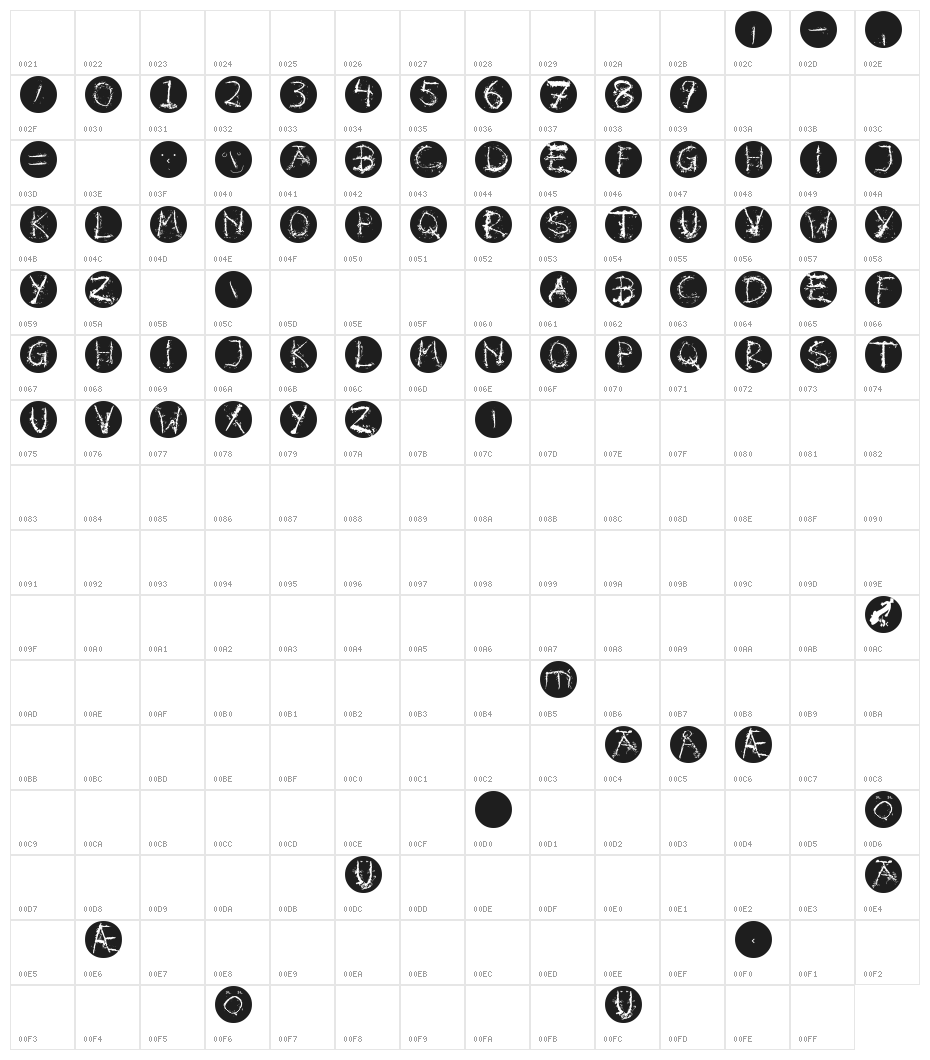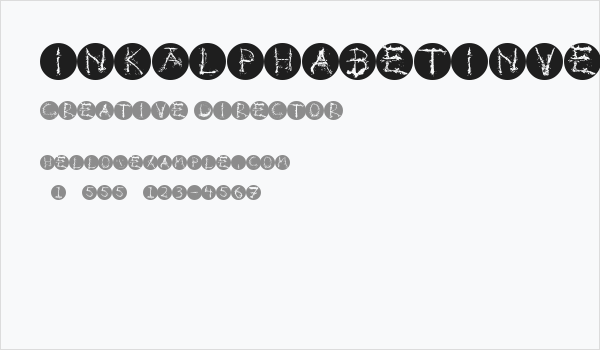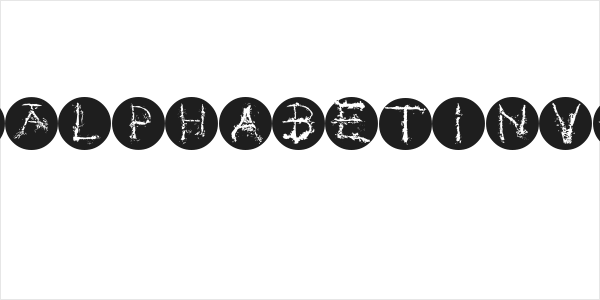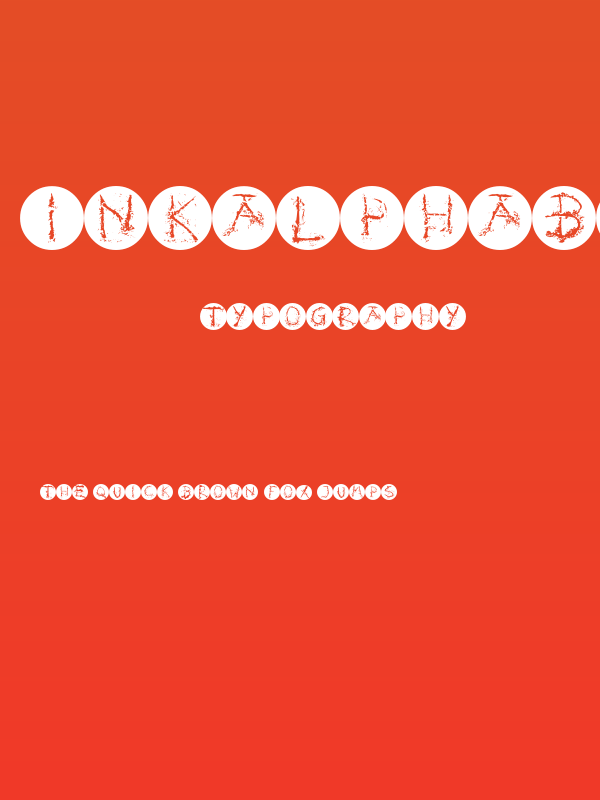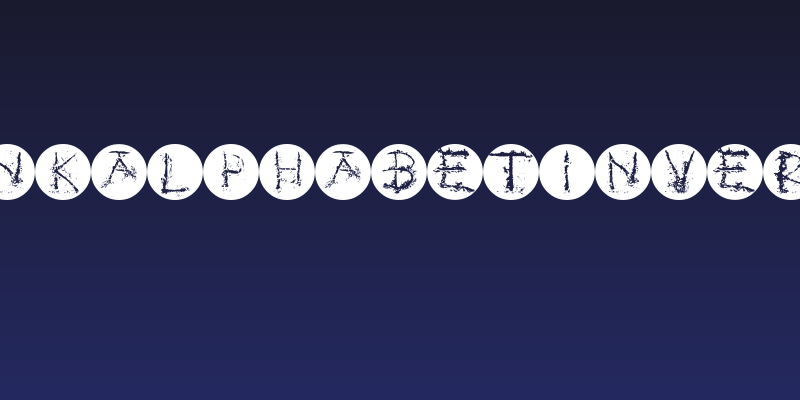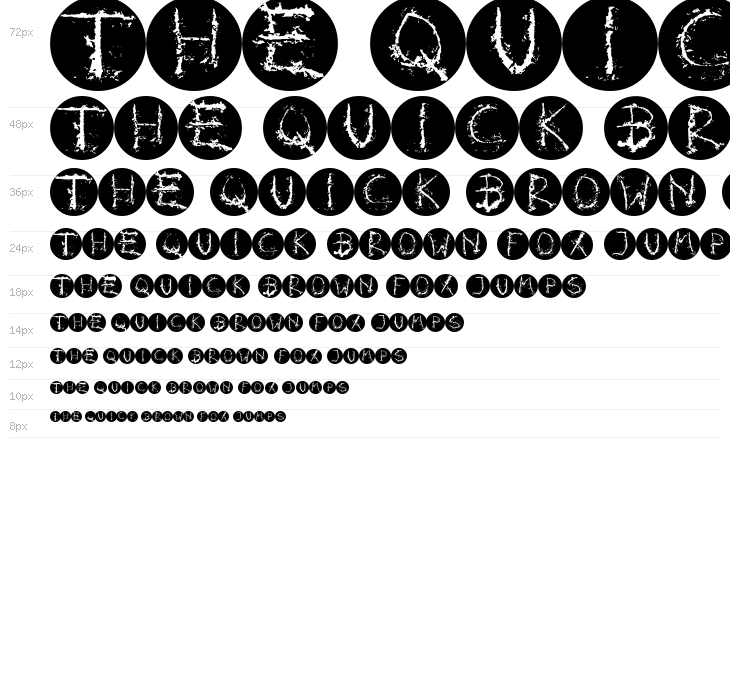
InkAlphabetInvers Font
| 分类 | Typewriter |
| 整体风格 | Vintage |
| 使用场景 | Logos, Headlines, Posters |
| 推荐项目 | Ideal for vintage-themed designs, posters, album covers, or any project needing a rugged, industrial aesthetic. |